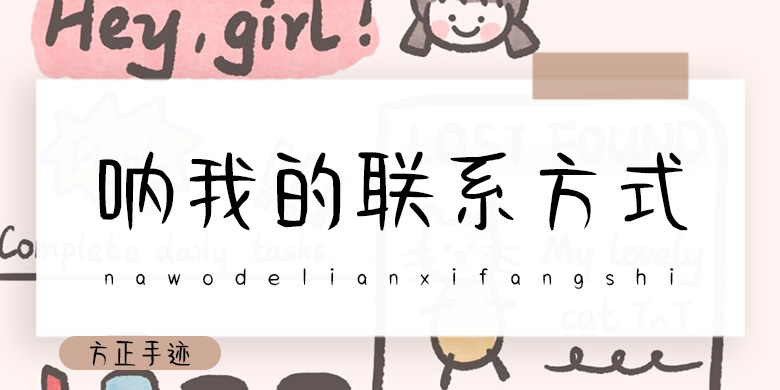
方正手迹-呐 我的联系方式
字体品牌: 方正手迹 设计师:王航 字体分类:创意书写 字体属性:精品字 字符集:简繁扩展(GBK) 发布时间: 2020
呐 我的联系方式是一款中文美术设计字体,字体笔画先重后轻,多取弧势,露出笔锋,对比强烈,显得流畅而又不失力度。字形整体重心偏下,头重脚轻,有趣可爱,是一款优秀的美术字体。适用于文艺、卡通、漫画类的书刊、品牌广告和产品包装设计,以及社交网络的个性化用字。